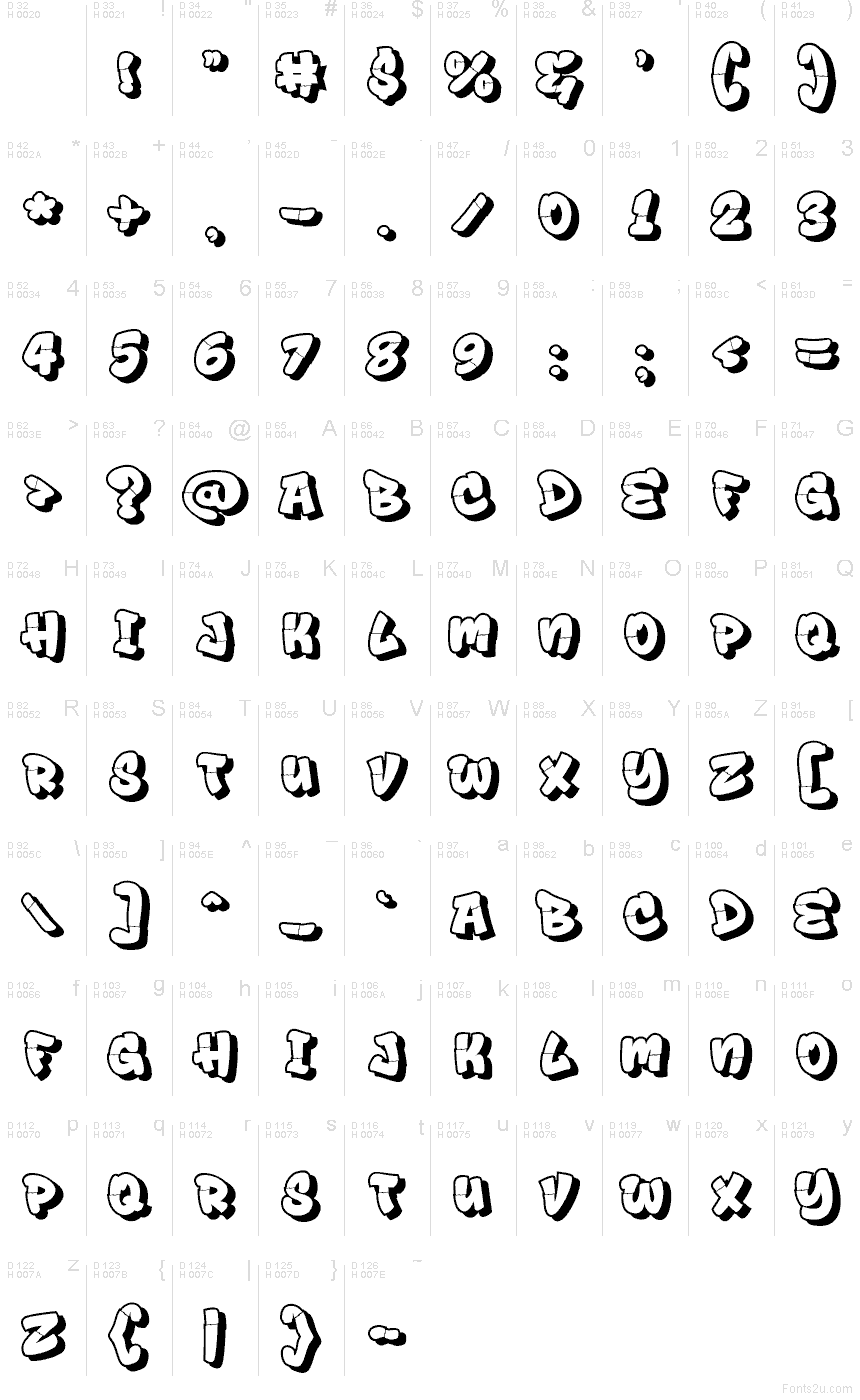
Il font Drop Shade Shadow di Muhammad Panji Ramdhani (Cikareotype) colpisce per le sue lettere graffiti in stile bubble e l'ombra integrata che fa letteralmente uscire ogni parola dalla pagina. Le forme arrotondate sono ariose e dinamiche, mentre l'ombra scura aggiunge una profondità immediata, come vernice fresca che si stacca da un muro. È un font graffiti gratuito che rimane leggibile anche quando componi frasi lunghe o lo allunghi in titoli d'impatto.
Drop Shade Shadow brilla su loghi streetwear, poster skate o hip-hop, miniature di YouTube, volantini di eventi, adesivi, copertine di album e packaging creativi. L'ombra crea una gerarchia visiva rapida, facendo risaltare i titoli brevi senza bisogno di effetti extra. Abbinalo a un carattere sans serif pulito e condensato per i dettagli e lascia che questo font gratuito venga utilizzato in grandi dimensioni affinché le sue curve morbide e la silhouette audace mantengano tutto il loro stile.